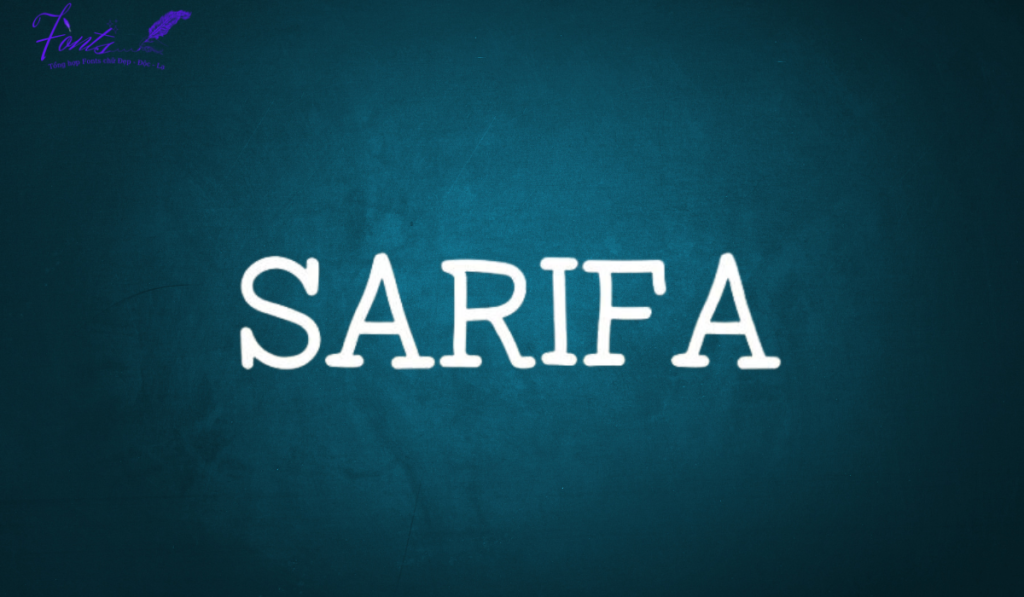
Font SVN Sarifa
Bộ Font: SVN
Phân loại: Thanh lịch, cổ điển
Kiểu chữ: Serif
Độ dày: Regular, Bold
Font SVN Sarifa thuôc bộ font SVN Việt hóa, là kiểu chữ có chân, thường được dùng để trình bày văn bản, poster.